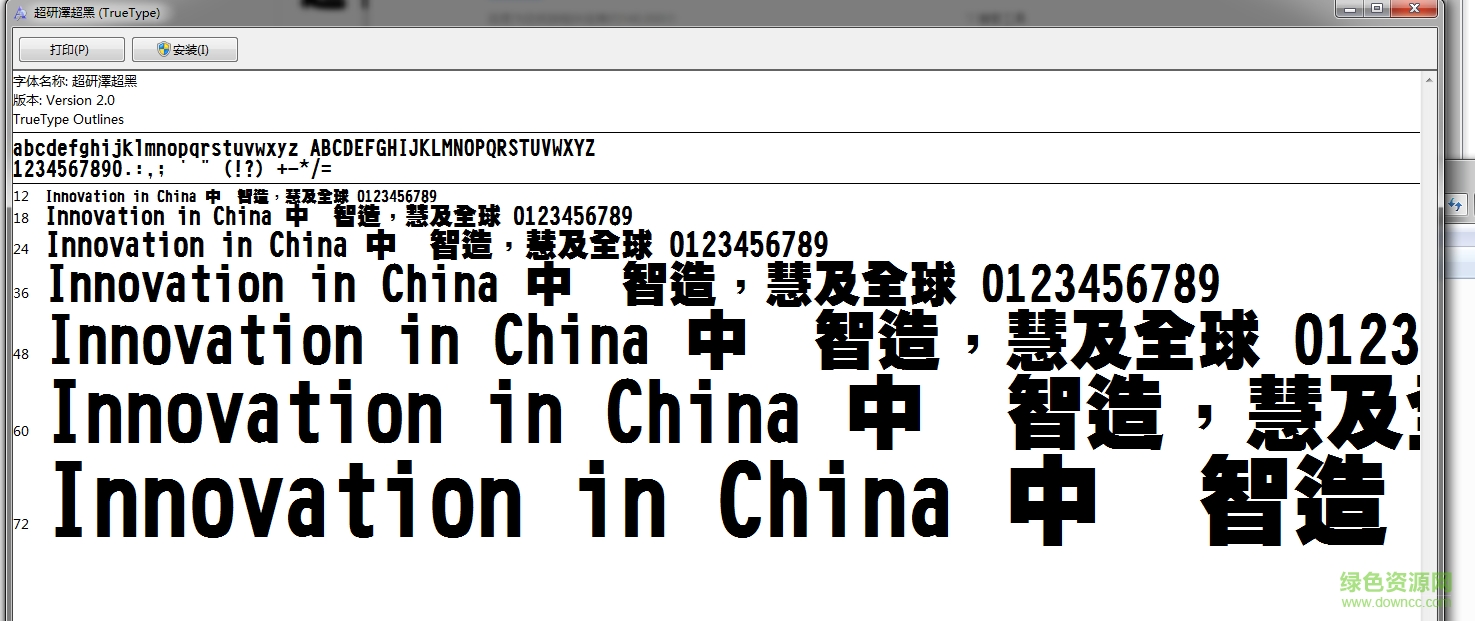
超研澤超黑體繁體
超研澤超黑體繁字體是一款許多朋友都在尋找的字體文件,改字體相對與其他字體更加的透黑、也較粗厚實,在PS、海報等處都受到了廣泛的使用,需要的用戶快到綠色資源網(wǎng)下載體驗吧
超研澤超黑體繁字體介紹
超研澤超黑體繁字體是生活中使用較多的字體,整體效果很黑,字體的線條粗,給人美觀